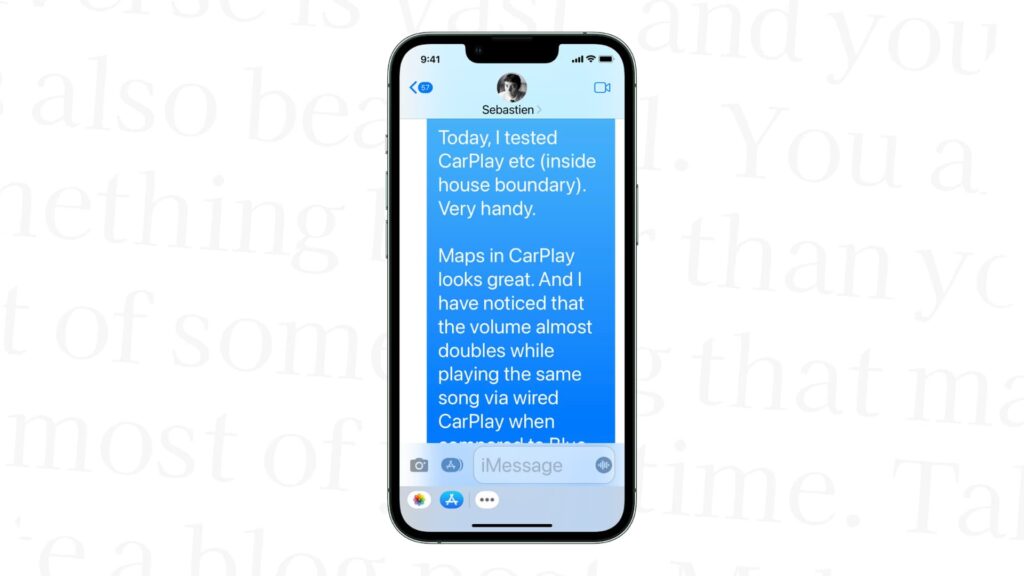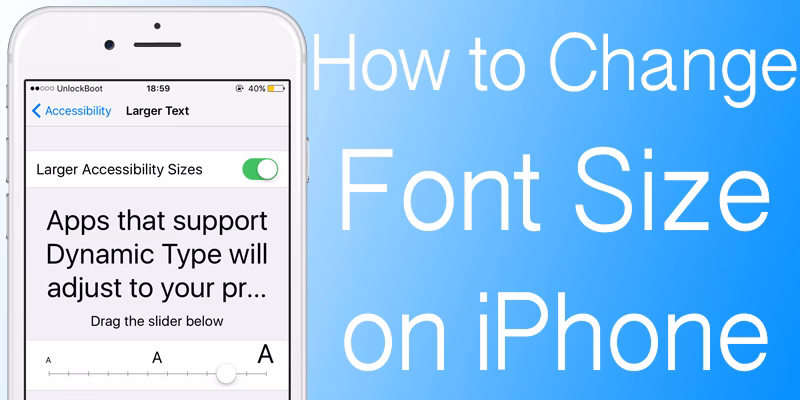
iMessage Skrifttyper: Forstå og Tilpas Dine Beskeder
Når du sender beskeder via iMessage, er det ikke kun ordene, der betyder noget, men også måden, de præsenteres på. En nøglefaktor, der bidrager til den samlede beskedoplevelse, er den skrifttype, der bruges i iMessage. Skrifttyper spiller en afgørende rolle i at formidle følelser, tone og personlighed i skriftlig kommunikation. Uanset om du ønsker at skrive en inderlig besked, dele en spændende opdatering eller blot deltage i en let samtale, kan valget af skrifttype have en betydelig indflydelse på, hvordan dine ord bliver modtaget. I denne artikel vil vi udforske de skrifttyper, der bruges i iMessage, og diskutere, hvordan du kan ændre dem, så de passer til din personlige stil. Men før vi dykker ned i skrifttypernes verden, lad os tage et nærmere kig på, hvad iMessage er, og hvorfor skrifttyper er vigtige på denne populære beskedplatform.
Hvilken Skrifttype Bruger iMessage?
Som resten af iOS bruger iMessage San Francisco skrifttypen. I 2015 gjorde Apple denne skrifttype tilgængelig og erstattede Helvetica Neue som operativsystemets standard skrifttype for iPhone, iPad og Mac. San Francisco har separate tekst- og displayversioner, der er skabt specifikt til at være læsbare på Apples digitale enheder. Dette betyder, at skrifttypen automatisk justerer sig til forskellige tekststørrelser for at sikre den bedst mulige læsbarhed i alle situationer, såsom en iMessage-diskussion eller en apps brugergrænseflade. San Francisco er kendt for sin klarhed, enkelhed og konsistens, hvilket gør den til et ideelt valg for mobilkommunikation.
Udviklingen af iMessage Skrifttypen
iPhone-besked skrifttypen har gennemgået flere ændringer siden introduktionen af den første iPhone i 2007. Oprindeligt var standard skrifttypen brugt i Beskeder-appen Helvetica, en meget populær typografi kendt for sit rene og moderne udseende. Helvetica tilbød en simpel og ligetil læseoplevelse, hvilket gjorde den til et passende valg til beskeder. Med udgivelsen af iOS 7 i 2013 introducerede Apple en ny systemskrifttype kaldet Helvetica Neue. Denne skrifttype havde et mere raffineret og elegant udseende sammenlignet med sin forgænger. Den indeholdt tyndere streger og forbedret læsbarhed, især på Retina-skærme med høj opløsning. Introduktionen af Helvetica Neue gav Beskeder-appen et frisk udseende og forbedrede den samlede visuelle oplevelse for iPhone-brugere. I 2019, med udgivelsen af iOS 13, introducerede Apple en ny standard systemskrifttype kaldet San Francisco. San Francisco blev oprindeligt udviklet til Apple Watch og senere adopteret som standard skrifttypen for iOS-enheder. Denne skrifttype blev specifikt designet til at optimere læsbarheden på små skærme og tilbød forbedret læsbarhed, især i længere tekstpassager. Introduktionen af San Francisco markerede et betydeligt skift i iPhone-besked skrifttypen og gav en mere moderne og ensartet typografisk oplevelse på tværs af Apple-enheder.
Kan Du Ændre Skrifttyperne i iMessage?
Ja, du kan ændre skrifttyperne i iMessage for at give samtalerne et personligt præg. Selvom Apple ikke direkte tilbyder en måde at ændre standard San Francisco skrifttypen i iMessage, er der metoder, du kan anvende. Dette indebærer brug af tredjepartsapplikationer eller tastatur-tilføjelser, der tilbyder et bredt udvalg af skrifttypevalg. Når du installerer disse programmer, bør du udvise forsigtighed, da ikke alle overholder Apples privatlivsregler.
Sådan Ændrer Du Tekstfremtoning i iMessages
Mens ændring af skrifttypen i iMessage kræver tredjepartsapps, kan du nemt ændre tekstattributter som størrelse, fed skrift og endda tilføje nogle effekter inden for iOS.
1. Ændring af Tekststørrelse
Hvis du vil ændre tekststørrelsen i iMessage:
- Gå til din iPhone- eller iPad-indstillinger.
- Tryk på “Skærm og lysstyrke” og vælg derefter “Tekststørrelse”.
- Her kan du trække skyderen for at justere tekststørrelsen efter din smag.
Denne ændring vil gælde for hele systemet og påvirke alle apps og systemgrænseflader, ikke kun iMessage. Dette er en systemdækkende ændring.
2. Gør Tekst Fed
For at gøre teksten fed:
- Gå til menuen “Skærm og lysstyrke” i indstillingerne.
- Der finder du indstillingen “Fed tekst”. Aktivér den, og din enhed vil kræve en hurtig genstart for at anvende denne indstilling.
Husk, at dette også gælder for hele systemet, ikke kun iMessage.
3. Tilføjelse af Effekter til iMessage Tekst
iMessage giver også brugerne mulighed for at sende beskeder med effekter som “slam”, “høj”, “blid” osv. For at bruge disse skal du skrive din besked og derefter trykke og holde sendeknappen (opadgående pil) nede. Dette åbner en menu med forskellige effekter. Vælg din ønskede effekt og tryk send.
Ændr Tekst Skrifttype med Tredjeparts App
Følg disse trin for at ændre skrifttypen i iMessage:
- Klik på følgende link for at hente appen “Color Text Bubbles on iMessage”: [Link til app - Bemærk: Da jeg er en AI, kan jeg ikke levere faktiske links. Du skal indsætte det relevante link her.]
- Åbn en hvilken som helst chat efter at have startet iMessage.
- For at få adgang til appens menu skal du klikke på App Store-ikonet, der er placeret ved siden af kameraikonet nederst til venstre på skærmen.
- Scroll og vælg appen.
- Tryk på knappen “Type Custom Message” for at tilføje en tilpasset besked eller vælg en af de forudbyggede beskeder i programmet.
- Hvis du vælger den anden mulighed, skal du trykke på tekstfeltet og indtaste det ønskede indhold.
- Vælg derefter et af ikonerne for et af følgende valg:
- Pil: For at ændre beskedens pil fra højre til venstre eller omvendt
- Boble: Vælg en hvilken som helst farve.
- Tekst: Vælg skrifttypestørrelse og farve.
- Hjerteikon: For at lave teksten om til et klistermærke, der kan bruges senere.